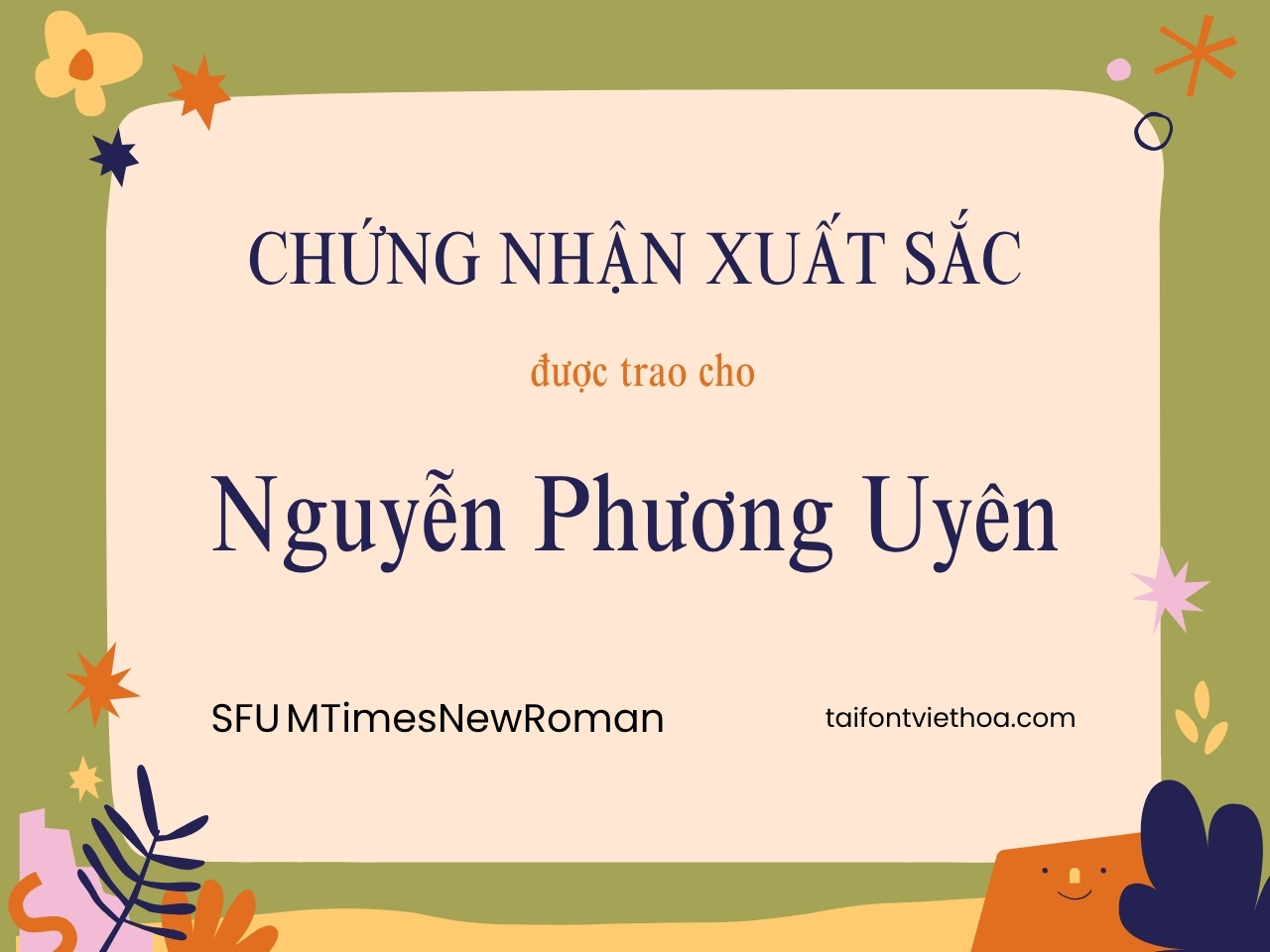
Font việt hóa SFU Mtimesnewroman
Giới thiệu về SFU MTimesNewRoman – Thư pháp cổ điển cho tài liệu chuyên nghiệp
SFU MTimesNewRoman là một biến thể Việt hóa của font Times New Roman – kiểu serif kinh điển được thiết kế bởi Stanley Morison và Victor Lardent năm 1931 cho tờ The Times ở London. Phiên bản SFU Việt hóa được đăng tải bởi người dùng Nguyễn Quỳnh Trâm Anh trên FontTiếngViệt.com vào ngày 04/10/2023; thông tin tác giả Việt hóa chưa được làm rõ. Ngoài hệ ký tự tiếng Việt, phiên bản quốc tế của Times New Roman hỗ trợ đầy đủ các ngôn ngữ sử dụng bảng Latin Extended – gồm tiếng Anh, Pháp, Đức, Ý,… với khả năng hiển thị chuẩn xác đa ngôn ngữ.
Đặc điểm thiết kế & ứng dụng ngành của SFU MTimesNewRoman
SFU MTimesNewRoman kế thừa đầy đủ đặc tính serif: đường nét mảnh nhưng sắc cạnh, tỷ lệ cân xứng giữa chân và thân chữ, tạo cảm giác trang trọng, đáng tin cậy. Phiên bản Condensed có nét hơi đậm và thu gọn, phù hợp cho tiêu đề trong không gian hẹp.
Về kỹ thuật, font hỗ trợ kerning tốt, có đầy đủ các ký tự Latin Extended-A, Basic Latin, những glyph đặc biệt như dấu câu, số, chữ in hoa nhỏ và một số ligature cổ điển. Font được lưu dưới định dạng TTF, hỗ trợ Unicode chuẩn nên dễ dàng dùng trong các phần mềm như Microsoft Word, Adobe InDesign, Illustrator, Photoshop.
Ứng dụng phù hợp: Soạn thảo tài liệu hành chính, giáo trình, luận văn, CV; thiết kế ấn phẩm sáng tạo như brochure, tạp chí, báo, poster sự kiện; banner quảng cáo chuyên nghiệp; thiết kế bao bì mỹ phẩm hoặc sách cao cấp.
Ngành nghề phù hợp: Giáo dục, xuất bản, truyền thông, luật & hành chính, tài chính – ngân hàng, thiết kế thương hiệu, dịch vụ sự kiện, thiết kế bao bì sản phẩm cao cấp.